Tren desain bergaya ala awal tahun 2000-an yang disebut Y2K masih populer tahun ini. Kombinasi desain dengan estetika retro dan futuristik menciptakan tampilan menarik dan fresh untuk era modern yang serba minimalis. Untuk menciptakan desain gaya y2k, gunakan elemen visual seperti font yang memiliki style futuristik dan retro yang menarik.
Tipografi Y2K identik dengan gaya huruf yang unik dan terkadang agak nyentrik, biasanya gaya retro dan futuristik identik dengan style y2k. Font yang cocok dengan tema desain y2k yang penuh warna dan elemen-elemen khas retro adalah tipografi yang tampil retro dan futuristik. Beberapa font untuk gaya desain y2k juga memiliki dekorasi khas retr seperti garis, tekstur dan outline.
6 FONT STYLE Y2K BERGAYA RETRO DAN FUTURISTIK
Style font untuk tema desain yang memiliki kombinasi elemen retro dan futuristik ini mencerminkan gaya desain pada awal teknologi digital. Elemen visual khas y2k juga memiliki style gambar kartun, lucu, penuh warna dan holografik style. Berikut beberapa font style y2k yang akan cocok dengan tema desain y2k tersebut:
Font Agora
Gaya font agora ini memiliki style futuristik yang sederhana tetapi berkesan canggih karena hurufnya yang tajam. Font ini memiliki gaya huruf yang tebal dan bergaya geometris kotak sehingga tampil futuristik. Desain bertema y2k bisa menggunakan font futuristik yang tebal ini sebagai font judul.
Desain y2k tak hanya menggunakan gaya retro tetapi juga style font futuristik karena desainnya memiliki visual teknologi digital. Gambar komputer generasi pertama dan beberapa teknologi lama menjadi ciri khas desain y2k. Itulah gaya font futuristik yang tajam seperti font tersebut juga cocok untuk tema desain Y2K.
Font 13-Misa
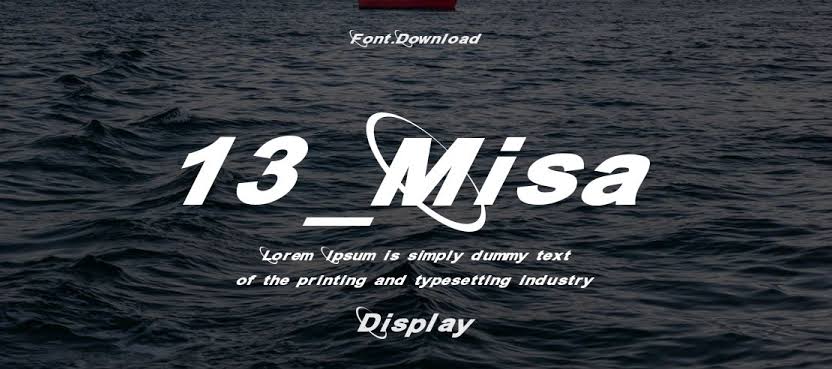
Gaya desain font Y2K juga identik dengan dekorasi garis-garis khas Y2K seperti pada font tersebut. Font 13_misa ini memiliki dekorasi lingkaran yang mengelilingi huruf kapital dalam jenis font ini. Dekorasi lingkaran seperti pada font tersebut identik dengan tema desain y2k.
Jika diperhatikan banyak style desain Y2K yang memiliki dekorasi lingkaran pada teks atau foto. Dekorasi garis-garis atau geometris dapat menciptakan estetika modern dan futuristik yang menarik. Gaya font ini bisa mencerminkan tema desain y2k yang menarik dan unik.
Classic Robot
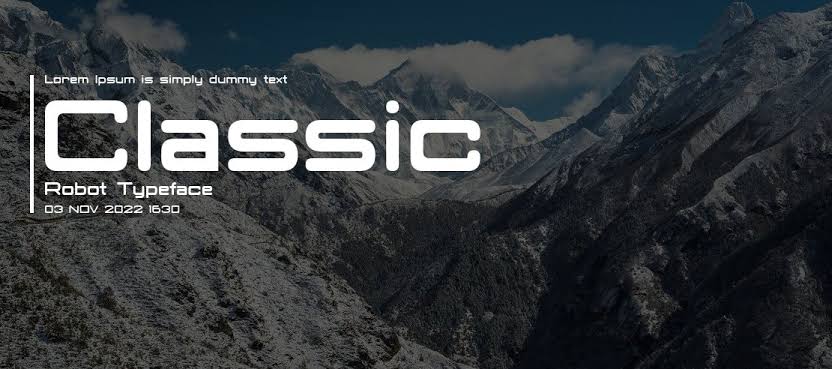
Gaya tipografi futuristik yang bersih dan tidak terlalu tebal juga bisa digunakan untuk desain bertema Y2K. Font classic robot ini memiliki gaya huruf futuristik yang sederhana dan bersih. Gaya huruf yang tidak tebal dan memiliki gaya techno ini tampil modern dan mudah dibaca.
Untuk tema desain y2k, gaya font yang tampil canggih dan modern ini bisa mencerminkan kesan futuristik pada desain. Style font y2k yang tampil futuristik akan mencerminkan teknologi modern yang canggih. Kombinasi font ini dengan warna holografik dan grafis komputer akan terlihat menarik.
Font Stora
Gaya font y2k, tak hanya tampil modern dan futuristik tetapi juga banyak menggunakan style font retro. Tipografi desain y2k yang memiliki gaya retro biasanya ciri font dengan garis bergelombang dan gemuk. Font tebal, bersih dan gemuk akan tampil ramah serta mudah untuk dibaca.
Desain y2k dapat menciptakan kesan fun dan playful dengan menggunakan gaya font seperti stora yang gemuk dan ramah. Gaya huruf pada font tersebut terlihat bergelombang dan menciptakan kesan menyenangkan. Padesain Y2K, font ini akan memberikan kesan retro dan fun terutama untuk kebutuhan desain stiker.
Font Magic Night
Gaya font retro akan relevan dengan tema y2k yang juga menggunakan estetika retro seperti warna pucat, gambar kartun dan lainnya. Style retro pada font yang cocok style desain y2k adalah dengan gaya huruf groovy yang tebal dan bulat. Font Magic Night ini lebih bulat dari font stora tetapi juga masih mudah dibaca.
Penggunaan font retro bulat dan groovy ini akan menciptakan desain y2k yang menyenangkan dan ramah. Dalam penggunaanya font ini seringkali akan diberi outline agar tampil lebih fun dan mudah dibaca. Gaya font tebal dan bulat ini akan menciptakan desain y2k yang ramah dan menyenangkan.
Font Molly Child
Retro groovy memang paling banyak direkomendasikan untuk jenis desain y2k yang memiliki tema warna-warna dan menyenangkan. Gaya desain y2k dapat memilih font groovy sebagai font judul pada tema desain yang fun atau playful. Tema desain y2k dengan font tebal dan bulat akan mudah dibaca dan menyampaikan informasi dengan baik.
Font molly child memiliki tampilan huruf bersih meski memiliki font yang groovy, tidak mengurangi keterbacaan teks. Gaya font ini akan relevan dengan kombinasi warna cerah, gambar kartun dan efek holografik yang menarik. Tambahan outline yang tebal dengan warna berbeda akan membantu meningkatkan keterbacaan pada latar belakang y2k yang terkadang ramai.
Warna metalik dan holografik efek akan menciptakan elemen visual dengan tampilan yang canggih. Efek holografik bisa mencerminkan kesan futuristik dan modern. Desain Y2K banyak menggunakan efek holografik dan metalik pada teks dan gambar tertentu.
Dalam menciptakan tema desain y2k yang populer dan tampil trendy ini pertimbangkan untuk menggunakan style elemen bergaya retro dan futuristik. Kombinasi dua style menciptakan y2k design terlihat menarik dan menjadi warna baru. Style elemen font, warna hingga gambar yang khas dengan tema y2k akan menciptakan desain grafis yang menarik.